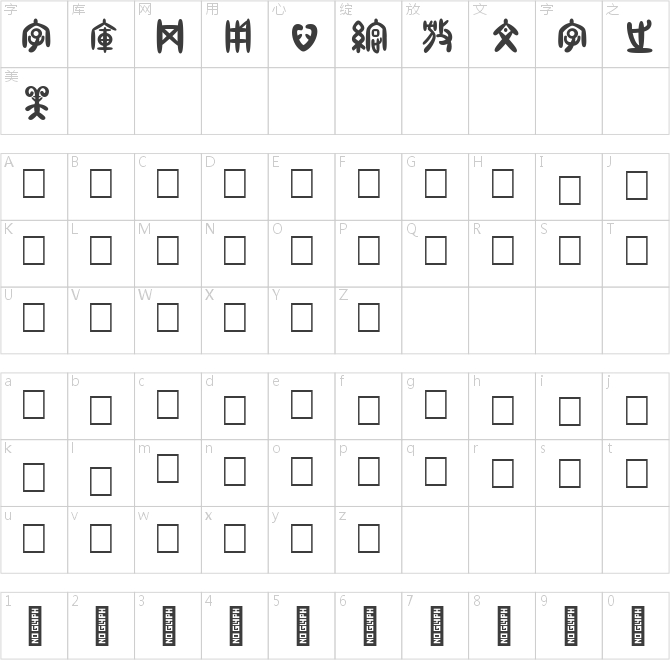
甲骨文
童心甲骨文是一款定位于兒童教育行業(yè)的細(xì)分字庫產(chǎn)品。它的整體風(fēng)格輕盈、圓潤(rùn),帶有強(qiáng)烈的手寫感和卡通特點(diǎn)。這些特點(diǎn)使得它非常適合用于教育相關(guān)的素材和物料。它的設(shè)計(jì)風(fēng)格適合吸引孩子們的注意力,讓他們更加樂于參與學(xué)習(xí)和探索。此外,童心甲骨文的字形清晰可辨,便于兒童初學(xué)者識(shí)字和書寫。無論是在教室、教材、海報(bào)還是其他教育資源中使用,童心甲骨文都能為兒童教育增添趣味和活力。